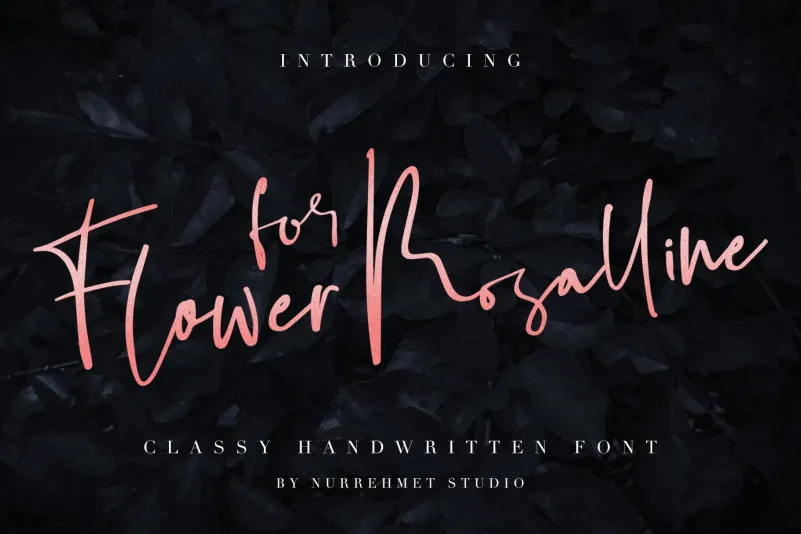
Flower For Rosalline Font – Download Grátis
A Flor For Rosalline é uma linda fonte escrita a mão que oferece um equilíbrio elegante entre suavidade e estilo. Através de sua natureza handwritten, essa fonte criará um impacto inegável em seus projetos, tornando seu design mais distintivo e personalizado. Seja para projetos de marca estilizados ou logotipos, embalagens de produto com textura única, frases escritas à mão ou cartões de convite de casamento, a Flor For Rosalline se destaca como uma escolha perfeita. Suas linhas sutis e suas características distintivas garantem um toque personalizado que certamente fará você suspirar. Perfecta para criar designs memoráveis e intrigantes!